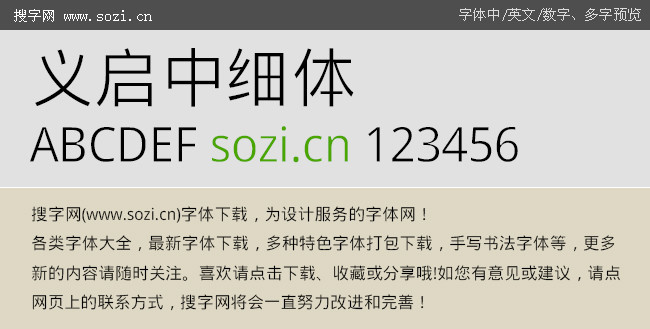
義啟中細(xì)體
搜字網(wǎng)提供一款義啟中細(xì)體中文字體下載,義啟中細(xì)體字體以簡約細(xì)膩的筆畫,給人非常有活力的感覺,整體效果工整有勁,非常耐看,筆畫與字形比例加大,字體重心在同一軸線上,增強(qiáng)了易讀性。能夠適用于藝術(shù)設(shè)計(jì)、包裝印刷、簽名設(shè)計(jì)、圖形設(shè)計(jì)等應(yīng)用。